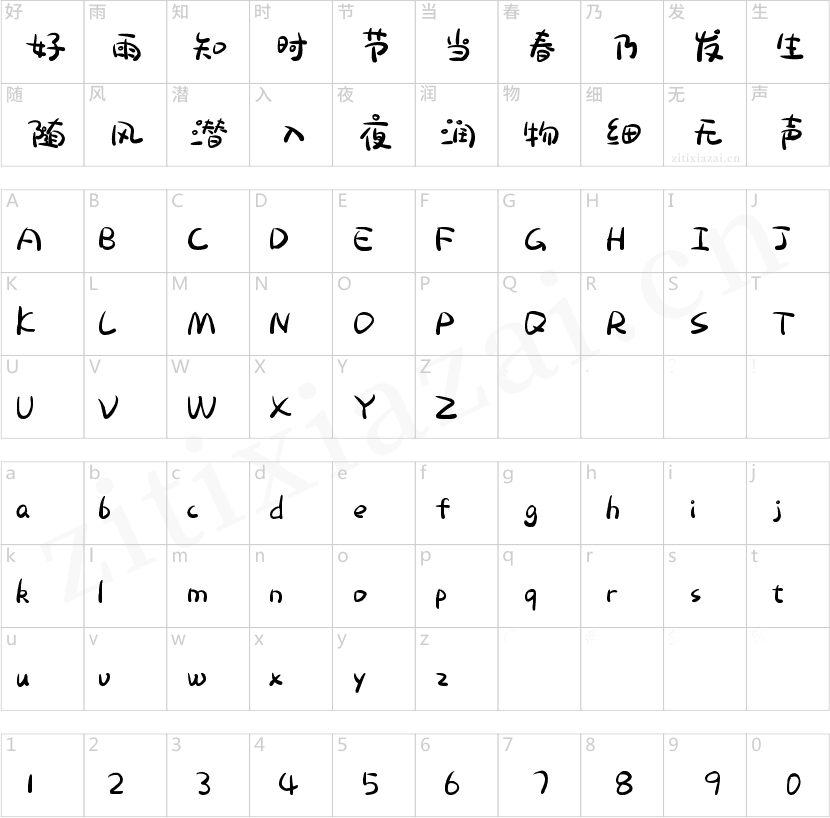
字魂萌趣露珠体
字魂萌趣露珠体,这款字体结构工整、笔画清晰,兼顾美观与易读性,适用于标题、正文、海报、包装、LOGO 等多种场景。字形优雅稳定,风格百搭耐看,适配日常排版与创意设计,让文字呈现更舒适、更具质感。字魂萌趣露珠体一笔一画,皆是细节,以均衡的比例、流畅的线条打造舒适视觉体验,字形端正大气,风格简约现代。无论是商业设计、品牌宣传还是日常排版,都能轻松驾驭,让文字更有格调与力量。字魂萌趣露珠体字体下载。